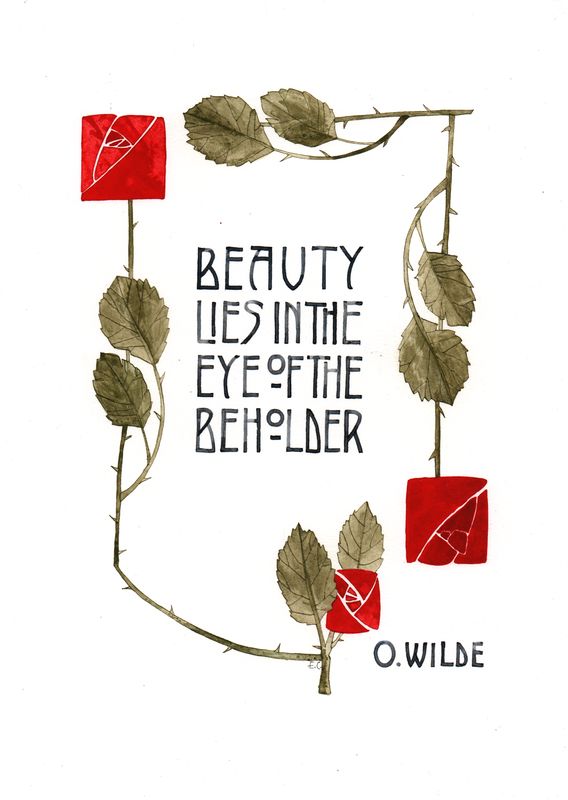
Art Nouveau :
ROYCROFT STYLE
L’art nouveau est un mouvement artistique qui court de la fin du 19ème au début du 20ème siècle. C’est un mouvement international qui se développe aussi bien en France, qu’en Belgique, Autriche, Allemagne, Royaume-Uni, Italie et États-Unis Ces multiples foyers communiquent entre eux, organisent des évènements internationaux et croisent leurs styles. Aux USA, à East Aurora N.Y., Elbert Hubbard fonde la Roycroft Community. Un de ses acteurs important, Dard Hunter, conçoit et coule les caractères d’une fonte qu’il utilisera dans les éditions ROYCROFT. On y retrouve des constantes des lettres Art Nouveau : le choix dominant de caractères en capitales et l’usage de la règle des tiers.
Sa patte personnelle se traduit par des verticales et horizontales rectilignes et des obliques galbées. Les extrémités des traits sont carrées ou en biais alignées sur la verticale ou l’horizontale. Les compositions intègrent des éléments végétaux stylisés, notamment la rose et ses tiges épineuses, empruntée à l’école de Glasgow – et côté couleurs, essentiellement du noir, du rouge et du vert.
Ce stage propose d’une part de reproduire cette écriture de Dard Hunter à la plume palette avec de légères retouches sur les extrémités des traits et d’autre part de réaliser une ou deux compositions « à la manière de » en reprenant les codes du Roycroft Movement en format A4.
Analyse et reproduction des formes d’une écriture Art nouveau américaine avec une variante.
Utilisation de la plume palette ronde
Utilisation d’éléments de composition (cadres, motifs, organisation) typiques du Roycroft Movement pour réaliser une ou deux productions.